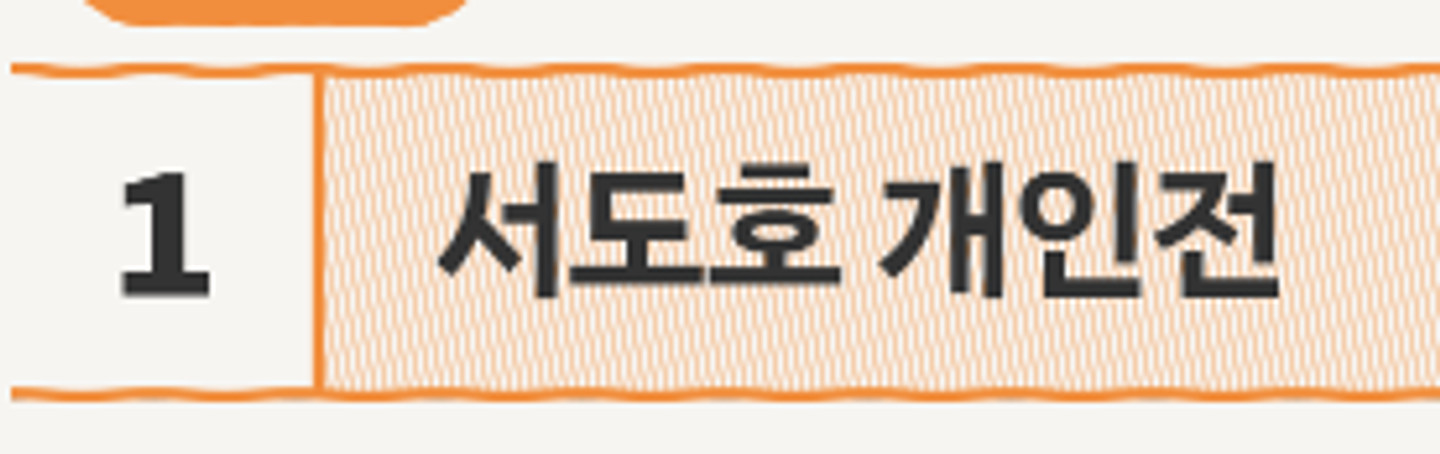
초코쿠키체
초코쿠키 C
입니더 기본 아니에요 https://blog.naver.com/jhb2581/222306324871
안녕하세요 이 글씨체 너무 귀여운데 무슨 폰트일까요? 루나파크 그림에서 본것같기도 한데 등록되어 쓸 수 있는 폰트인가요? 답변 달아주시는분 미리 감사드립니다